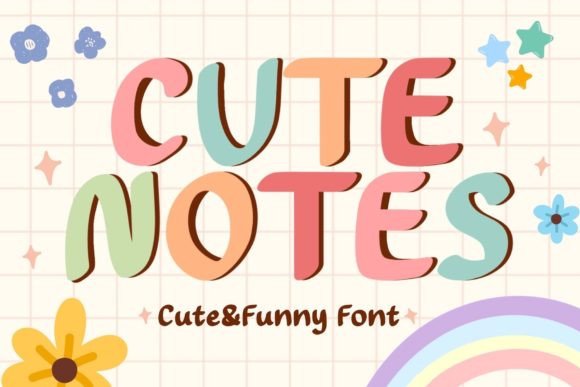
Cute Notes
適切なデザイン要素を見つけるのは難しい場合がありますが、Cute Notesは作品を即座に引き立てる優れたコレクションを提供します。
POD(オンデマンド印刷)製品、結婚式の招待状、またはソーシャルメディアのグラフィックを作成している場合でも、Cute Notesは理想的です。